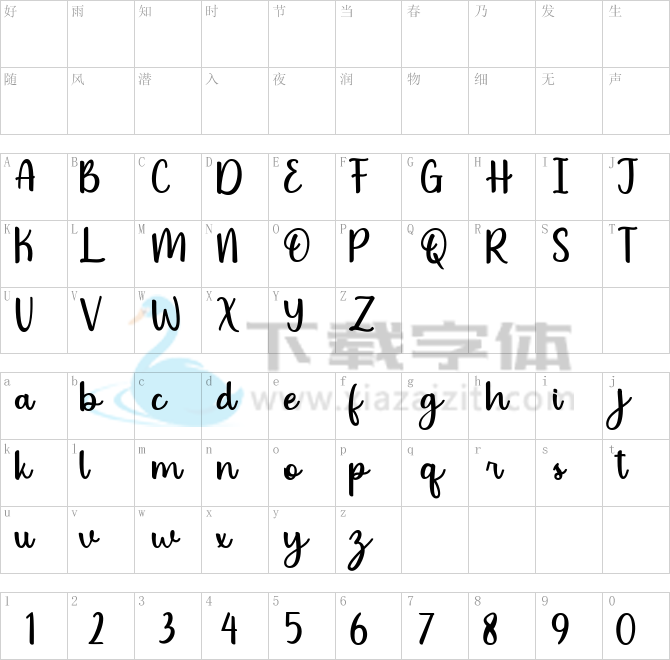
Arteliria Script.ttf字体下载,这款字体结构工整、笔画清晰,兼顾美观与易读性,适用于标题、正文、海报、包装、LOGO 等多种场景。字形优雅稳定,风格百搭耐看,适配日常排版与创意设计,让文字呈现更舒适、更具质感。Arteliria Script.ttf字体下载一笔一画,皆是细节,以均衡的比例、流畅的线条打造舒适视觉体验,字形端正大气,风格简约现代。无论是商业设计、品牌宣传还是日常排版,都能轻松驾驭,让文字更有格调与力量。Arteliria Script.ttf字体下载字体下载。